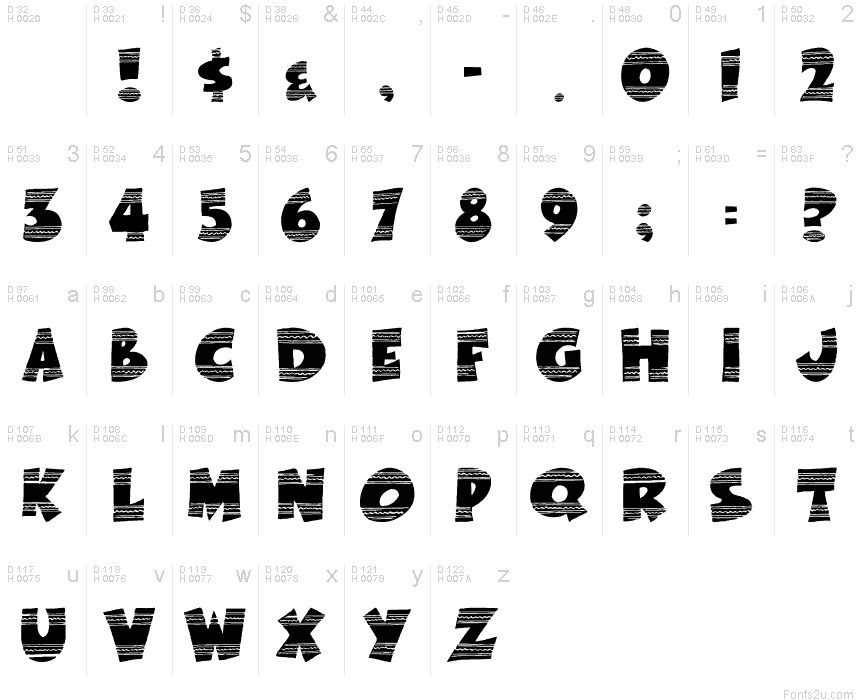
AwesomeClipartforKidsによる「EasterFunbyTom」は、大胆なイースターエッグを太い文字にカットしたような、無料の装飾系ディスプレイフォントです。ジグザグやストライプ、ドット柄で包まれた厚みのある黒いシェイプは、まるで手描きの卵でいっぱいのバスケットのような雰囲気を与えてくれます。忙しいけれど遊び心のあるテクスチャなので、たった一言でもバナーやタイトルが手作りのホリデー・プロジェクトのように仕上がります。
EasterFunbyTomを使えば、イースターパーティーの招待状、エッグハントのポスター、学校のワークシート、子供向けの活動パック、ソーシャルメディア用グラフィック、グリーティングカードなどの見出しに、春の空気をすぐに吹き込むことができます。この無料フォントは、パターン化されたストライプが映えるよう、大きくて大胆に使用するのが最適です。本文には、シンプルな丸みを帯びたサンセリフ体を組み合わせることで、レイアウトを圧倒することなくイースターのテクスチャの楽しさを活かせます。